Desain sertifikat harus dibuat menarik mungkin menyesuaikan temanya. Hal ini karena sertifikat merupakan salah satu dokumen resmi yang diberikan ke seseorang ataupun organisasi atas suatu pencapaian tertentu. Contohnya saja seperti sertifikat menyelesaikan kursus, workshop, penghargaan dan masih banyak yang lainnya. Namun untuk bisa membuat desain sertifikat yang baik, Anda harus memperhatikan beberapa hal penting.
Salah satu di yang harus Anda perhatikan adalah menentukan jenis font. Karena tidak semua font cocok digunakan untuk membuat desain sertifikat. Beberapa jenis font yang cocok untuk desain sertifikat umumnya memiliki bentuk unik, rapi dan mudah terbaca. Tapi ada juga yang menggunakan font tegak bersambung. Hal ini kembali lagi ke tema sertifikat yang akan diberikan. Kalau begitu mari kita lihat daftar font sertifikat keren yang bisa Anda download secara gratis berikut ini!
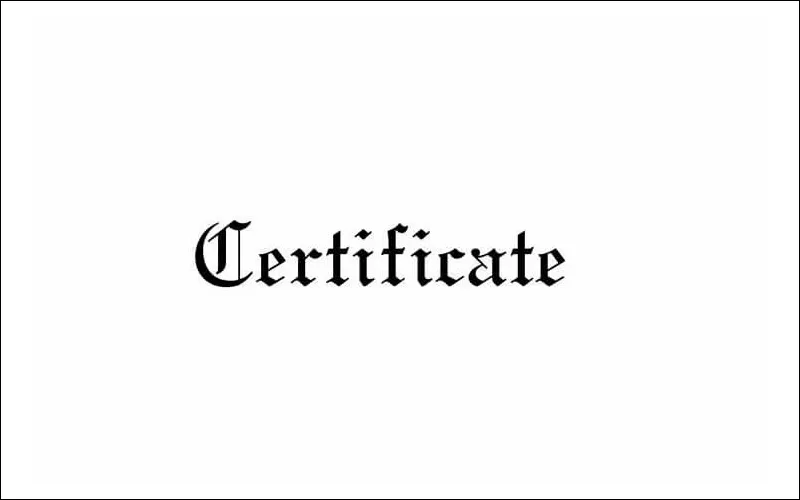
Pertama Anda bisa menggunakan font Certificate. Font ini yang paling umum digunakan untuk membuat desain sertifikat. Jadi, kalau Anda ingin yang biasa digunakan orang banyak, bisa memakai font Certificate ini.
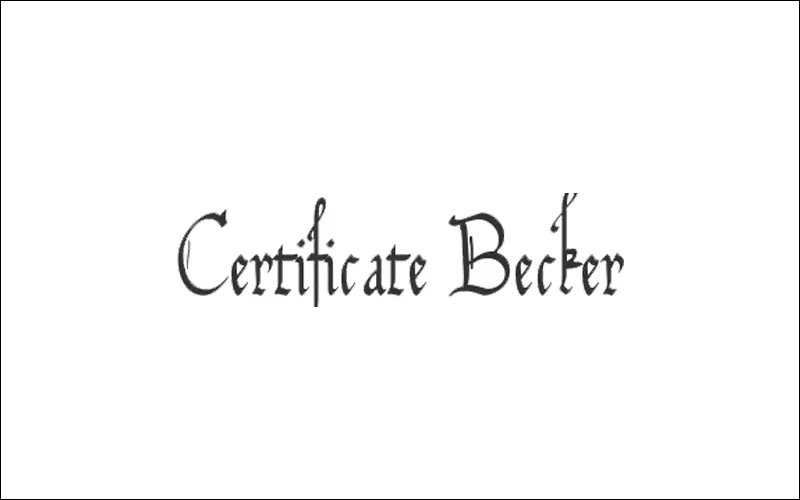
Kalau ingin yang sedikit berbeda, Anda bisa menggunakan font Certificate Becker. Bedanya, di font Certificate Becker ini terdapat garis pada beberapa karakternya.
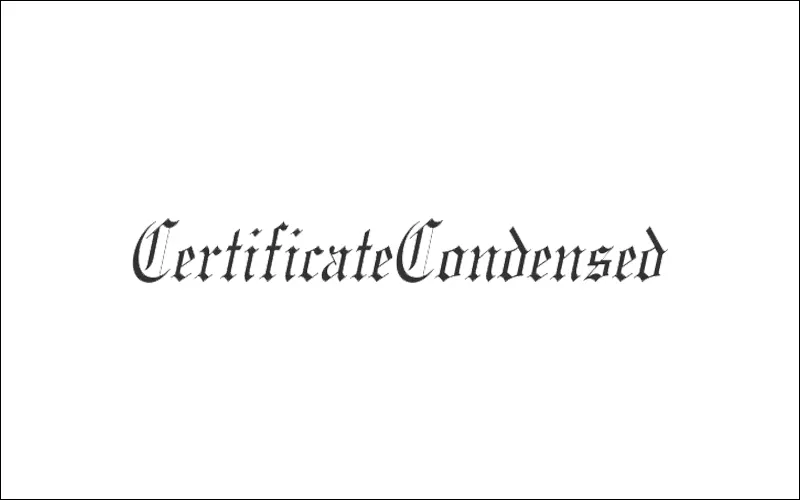
Lalu ada juga font Certificate Condensed. Font sertifikat ini punya bentuk yang sedikit miring. Dari segi bentuk, font ini tidak berbeda jauh dengan Certificate Font.
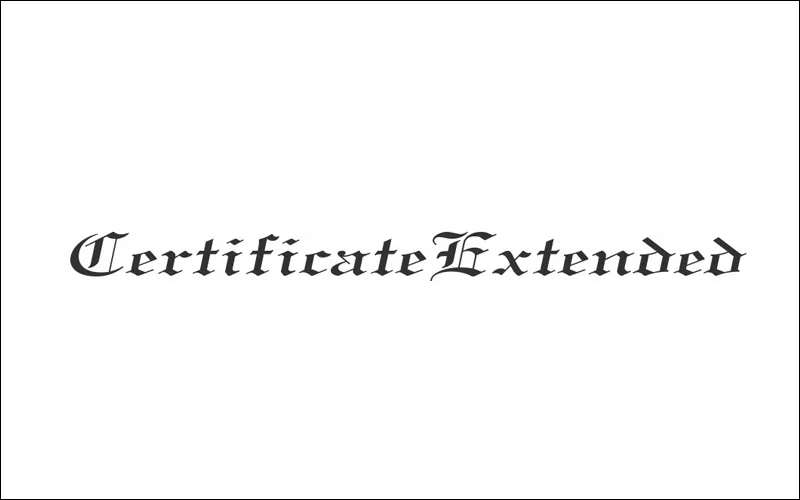
Kalau Anda mencari font sertifikat dengan indent tinggi, bisa gunakan Certificate Extended. Sesuai dengan namanya, font sertifikat ini memiliki jarak yang cukup jauh di setiap karakternya.
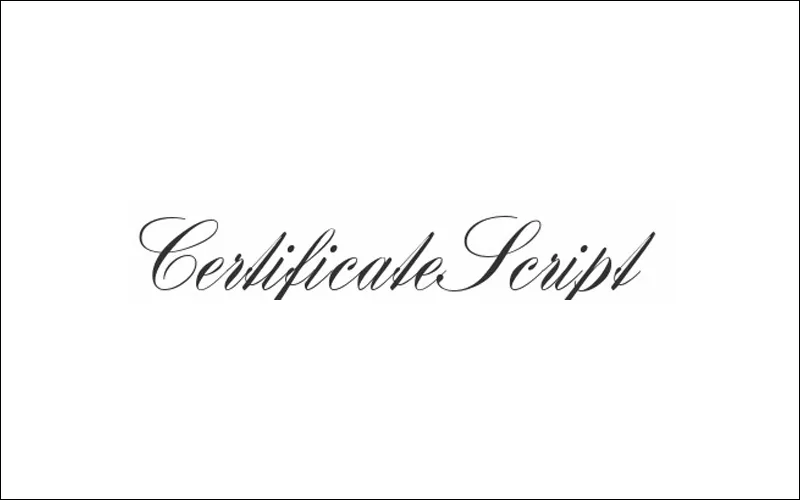
Sedangkan kalau ingin menggunakan font sertifikat tegak bersambung, Anda bisa memilih Certificate Script. Bentuknya yang tegak bersambung dan sedikit miring ini banyak juga digunakan desainer untuk membuat sertifikat resmi.
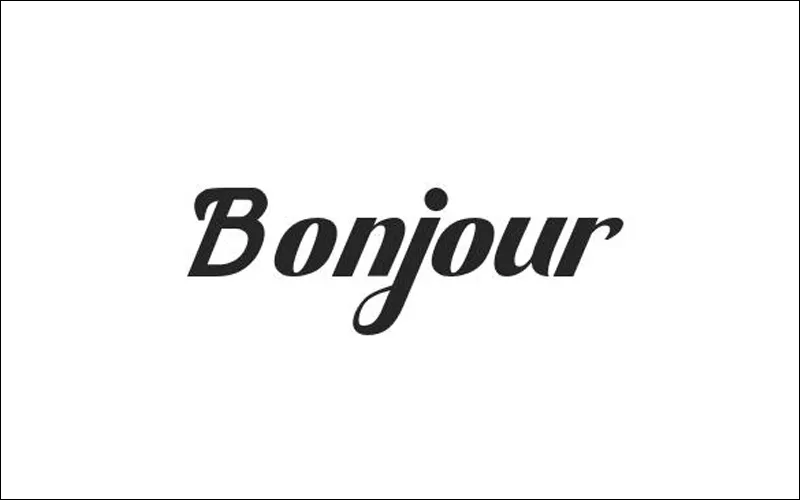
Bonjour adalah font dengan desain sederhana dan bisa dipilih untuk membuat sertifikat. Font ini punya ketebalan yang cukup tinggi di tambah desain coretan pada beberapa karakternya.
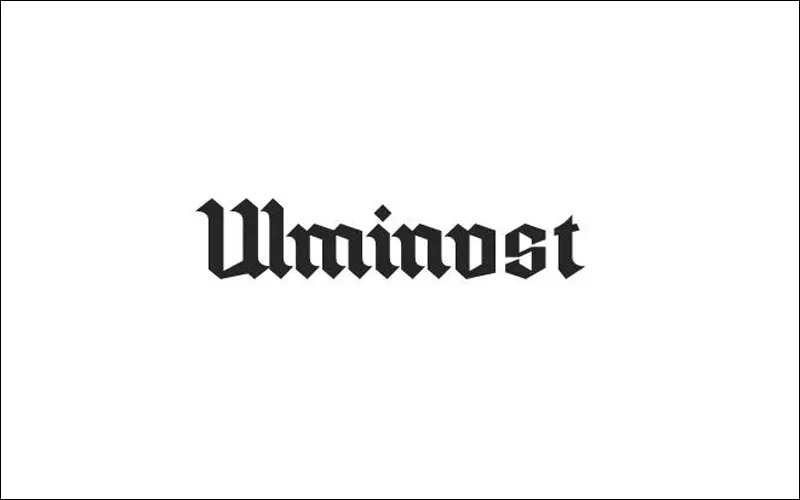
Selain Bonjour, Anda bisa menggunakan Ulminost untuk membuat sertifikat. Font ini punya dekorasi yang lebih kompleks. Di mana setiap ujung karakter punya coretan tebal pendek, sehingga bisa membuat sertifikat terlihat cantik.
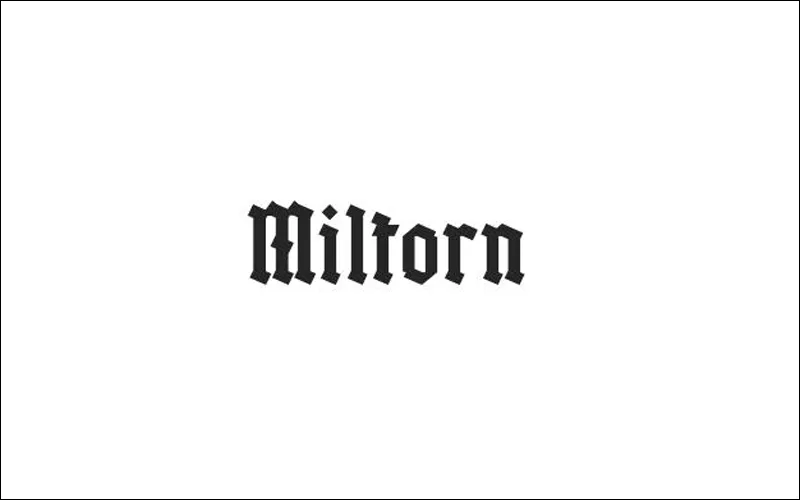
Tidak berbeda jauh dari font sebelumnya, Miltorn juga punya dekorasi kompleks di setiap karakter. Seperti yang bisa Anda lihat, font Miltorn ini ada desain unik berupa tekanan pulpen di setiap ujung karakternya tanpa coretan.
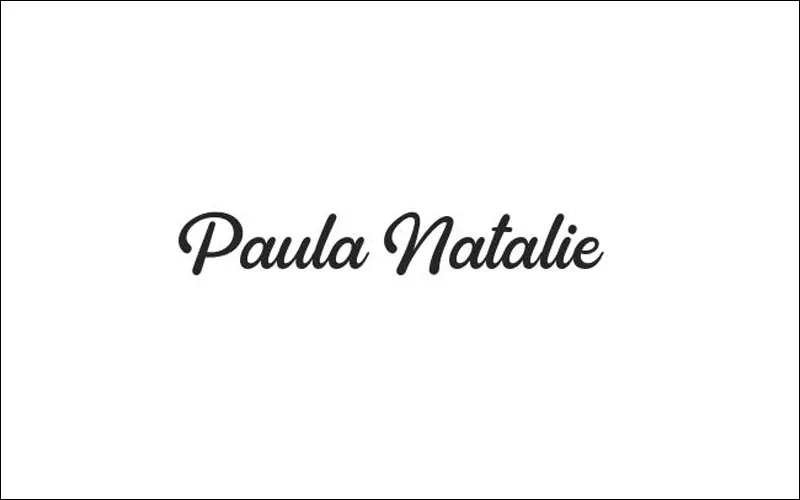
Umumnya, Paula Natalie biasa dipilih untuk membuat sertifikat dengan tema parenting. Alasannya karena karakter di setiap font Paula Natalie terlihat feminin dan cursive.
Sedangkan untuk sertifikat tema olahraga, bisa menggunakan font Flokison. Font ini punya desain sederhana, namun terlihat elegan. Itulah mengapa banyak yang menggunakan font Flakison ini untuk membuat sertifikat tema olahraga.
Modesty Script cocok dipilih untuk membuat sertifikat seminar dengan tema perempuan, parenting dan sejenisnya. Karena font ini punya bentuk yang manis dengan feminin.
Selanjutnya ada font Berseker. Font ini punya efek shadow line di setiap karakternya. Menjadikan font ini punya desain unik dan cocok dipilih untuk membuat desain sertifikat.
Rengkox merupakan salah satu font yang cocok untuk membuat desain sertifikat. Mulai dari sertifikat penghargaan karyawan terbaik, seminar, workshop dan tema pembelajaran lainnya.
Tidak jarang kita melihat sertifikat yang menggunakan font tegak bersambung. Jika Anda tertarik membuat sertifikat dengan jenis tersebut, bisa menggunakan font Silentha. Font ini punya karakter tipis dan formal.
Mirip seperti Rengkox, Font Roback juga cocok dipilih untuk membuat desain sertifikat. Kalau Anda bisa memadukannya dengan warna yang bagus, desain sertifikat dengan font Roback akan menjadi terlihat elegan.
Biasanya font Krinah dipilih untuk membuat isi dari desain sertifikat. Isi yang kami maksud, seperti nama penerima sertifikat dan judulnya.
Font Amandez biasa dipilih untuk membuat sertifikat penghargaan sekolah dan kampus. Karena desain dari font Amandez ini mirip seperti pita di setiap karakternya.
Kalau Reshon umumnya dipilih untuk membuat sertifikat seminar dan workshop. Supaya terlihat menarik, umumnya font Rheson ini dipadukan dengan warna gelap. Sedangkan fontnya berwarna terang.
Anda bisa memilih font Amandez, Radiant Antique, Forte, dan The Cheese.
Anda harus bisa memilih font yang tepat sesuai tema sertifikat, pemilihan kombinasi warna dan memanfaatkan space kosong.